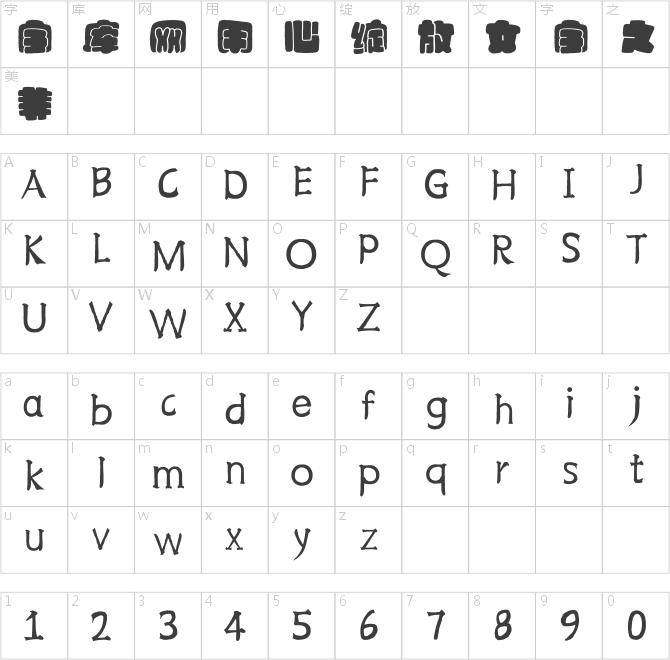
字體名稱: 邯鄲窩窩簡體
邯鄲窩窩簡體
邯鄲窩窩簡體介紹
作品的獨特性:邯鄲窩窩簡體以韓紹杰老師創作的電腦美術字制作而成。
主要特征該字體筆畫粗壯,兩端呈圓頭,筆畫相交緊密,呈凹陷窩狀,中宮比較緊湊。黑字面大,字型粗曠,結構嚴謹,重心一致;筆劃制作精良,線條剛柔相濟,簡潔有力。閱讀舒適流暢,適用于報刊、雜志和書籍中的大型標題。
主要特點:邯鄲窩窩簡體,筆畫粗狀、橫清晰、突出醒目等特點, 有著非常烈的